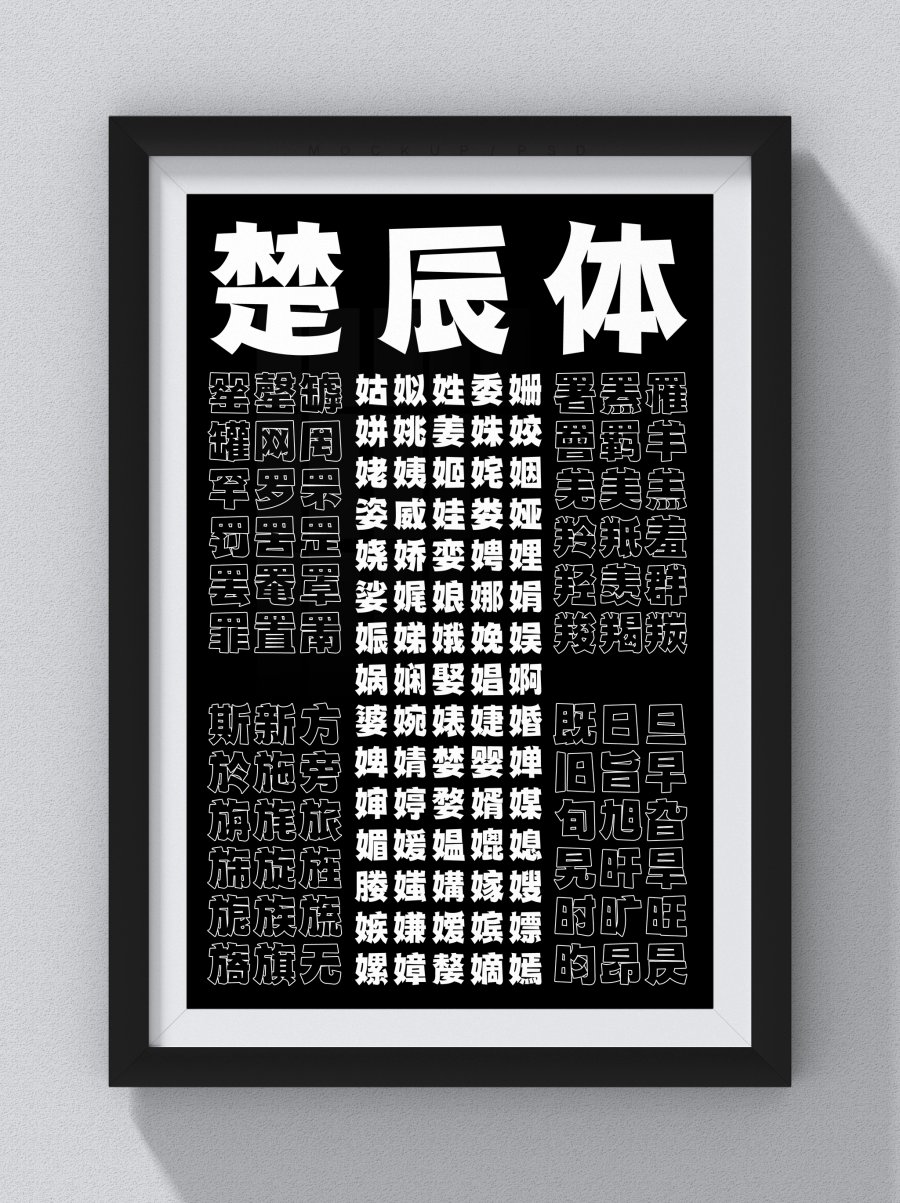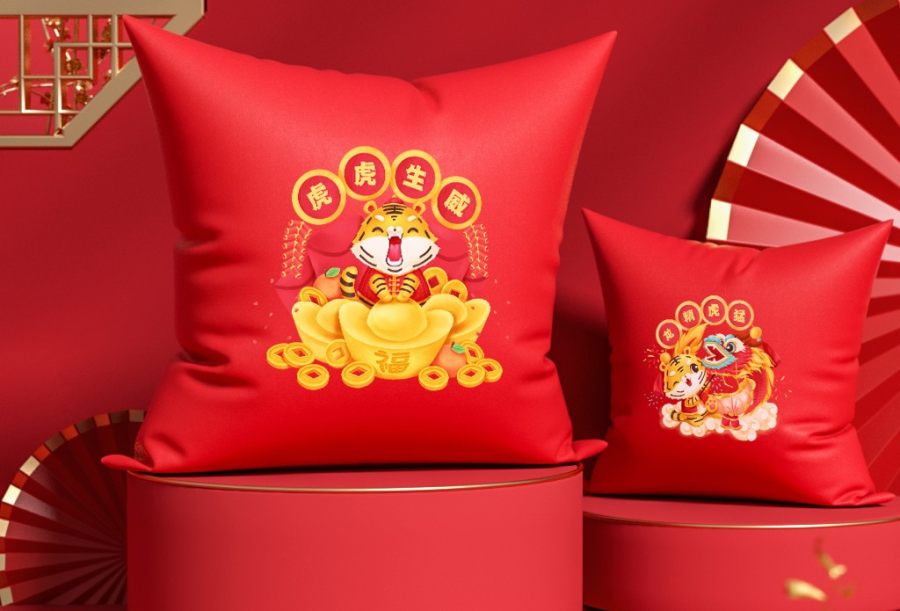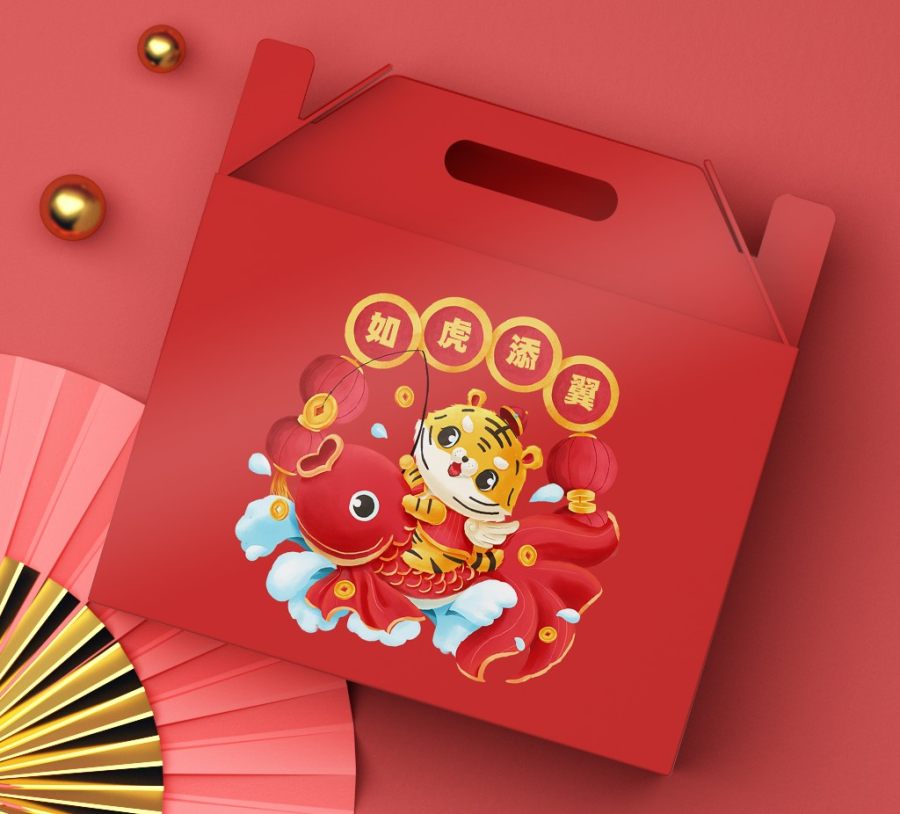
GB2312 中文简体字库,包含6781个中文字体+拉丁+符号
“楚辰体”的字能在轻松时尚的氛围中体现,粗黑为字形基础,不规则的笔画,在排版时能表现跳跃的节奏感。轻快自然的特征能让标题和广告语更加醒目生动。该字由著名字体设计师丞言老师耗时2年独自完成创作,由字体视界对外公开首发,供个人免费商用,企业需付费商用授权使用。